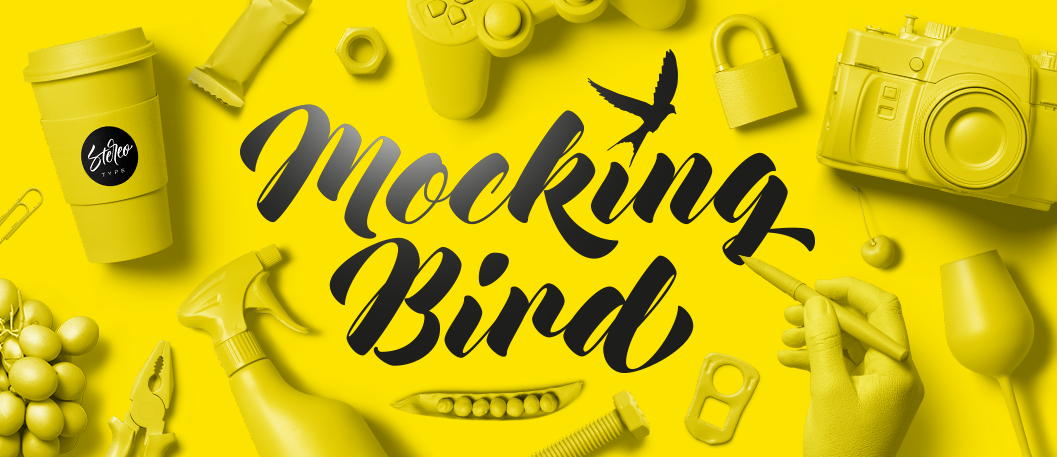
A fonte Mocking Bird é uma elegante escolha para designers que buscam uma combinação única de sofisticação e frescura. Desenvolvida pela StereoType, esta script font tem um visual marcante com curvas sedutoras, oferecendo um toque inovador às criações digitais. A versão comercial completa da Mocking Bird vem equipada com uma coleção impressionante de 62 alternativas de caracteres e ligações contextualizadas, tornando-a uma opção irresistível para aqueles buscando a perfeição em sua tipografia. Ideal para criar um design visual atrativo e sofisticado, essa fonte é certamente um recurso indispensável no arsenal do designer.